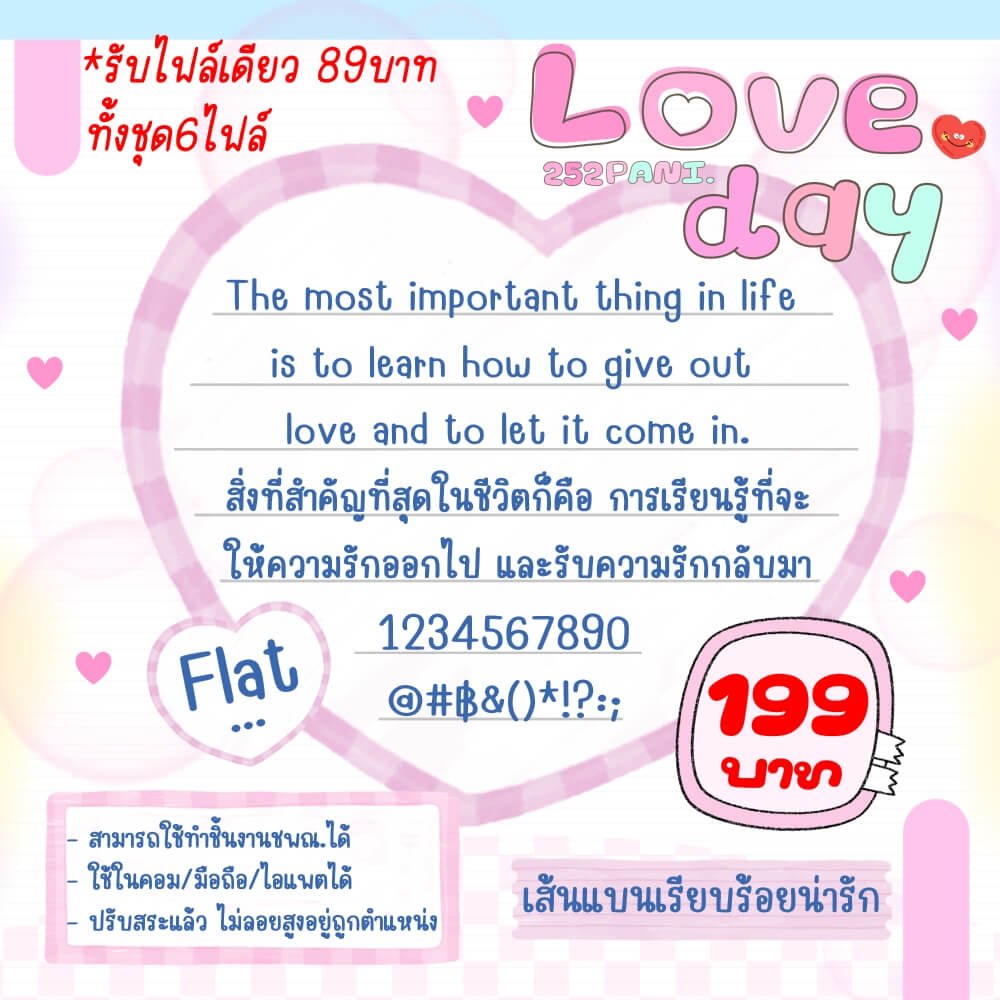
252PANI.Loveday
ฟอนต์ 252PANI.Loveday แจกฟรี!! ตัว Demo – แนวเรียบร้อย ขนาดตัวกำลังดี เหมาะกับงานหลากหลายแบบ
ฟอนต์มี 6 ไฟล์ – น้ำหนัก บาง ปกติ หนา เอียง แบน ภาษาน่ารัก